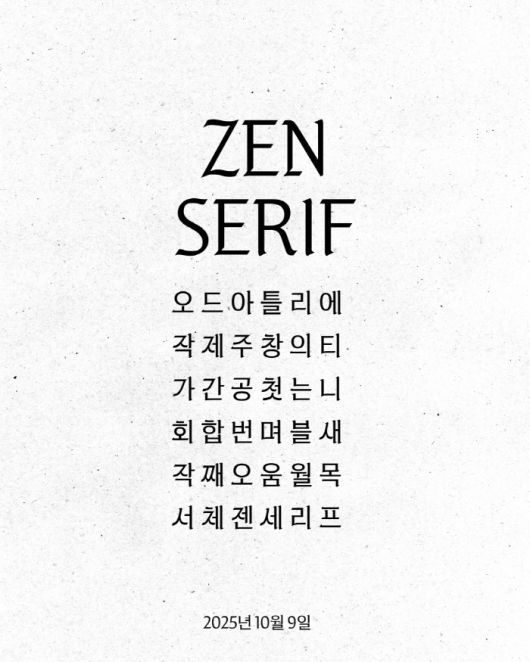
9일 소속사 OA엔터테인먼트(ODDATELIER, 이하 OA)는 공식 홈페이지와 SNS 채널을 통해 더 많은 사람들이 한글을 편리하고 아름답게 사용할 수 있길 바라는 마음을 담은 신규 폰트 '젠 세리프' 출시 소식을 알렸다.
OA는 메타(Meta)와의 협업을 통해 인스타그램 숏폼 영상 편집 앱 에디트에 한글 폰트를 최초로 등록, 9일부터 전세계 모든 앱 사용자가 해당 신규 폰트를 자유롭게 사용할 수 있도록 했다.
'젠 세리프' 폰트는 전통의 미감과 현대적 감각을 제니와 OA의 정체성으로 담아 전 세계에 한글의 아름다움을 알리기 위해 출시된 것으로, 한글날을 맞이해 폰트가 출시돼 더욱 의미가 뜻깊다.
'젠 세리프'는 고정된 이미지를 벗어나 오늘의 시각에서 새롭게 창작된 폰트다. 장식을 최소화해 본질을 살리고, 딱딱한 인상을 덜어내면서 유연한 곡선을 더해 OA 특유의 섬세한 예술성을 담았다. 서양의 전통 서체인 블랙레터와 한글을 결합해 누구도 시도하지 않았던 낯선 조합을 완성했다.